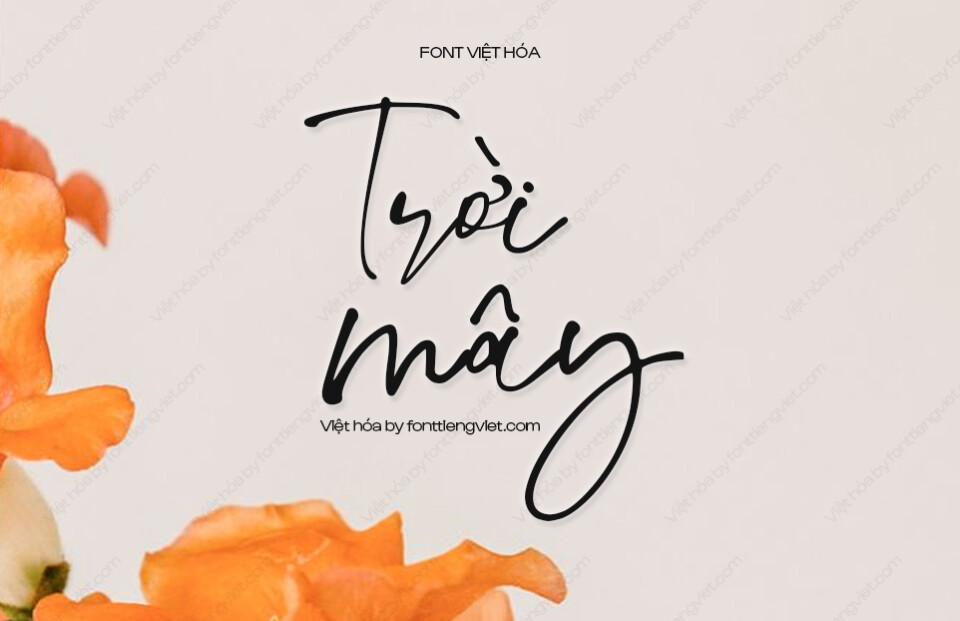
Giới thiệu về bộ Font Việt hóa 1FTV Sidneyland
Trong thế giới đồ họa hiện đại, việc tìm kiếm một bộ Font Chữ vừa mang nét tinh nghịch vừa giữ được sự chuyên nghiệp là điều không dễ dàng. Font Việt hóa 1FTV Sidneyland chính là giải pháp hoàn hảo cho các bạn học sinh và giáo viên khi muốn tạo ra những ấn phẩm học đường sinh động. Với đường nét thanh mảnh nhưng vẫn chắc chắn, bộ phông này giúp truyền tải thông điệp một cách nhẹ nhàng và gần gũi nhất. 1FTV Sidneyland được đội ngũ thiết kế tối ưu hóa hoàn toàn để hiển thị tốt trên các phần mềm soạn thảo văn bản và đồ họa phổ biến hiện nay.
Ưu điểm nổi bật của Font Việt hóa 1FTV Sidneyland
Thiết kế độc đáo và hiện đại
Điểm mạnh nhất của Font Việt hóa 1FTV Sidneyland chính là sự linh hoạt trong ứng dụng. Các ký tự được chăm chút tỉ mỉ, giúp việc đọc trở nên dễ dàng hơn dù trên màn hình máy tính hay khi in ấn. Bộ font này cực kỳ phù hợp để thiết kế bìa sách, nhãn vở, hoặc các bài thuyết trình PowerPoint trong lớp học, mang lại cảm giác vui tươi và tràn đầy năng lượng sáng tạo cho người xem.
Hỗ trợ tiếng Việt hoàn chỉnh
Khác với các bộ font nước ngoài thường bị lỗi dấu khi gõ tiếng Việt, Font Việt hóa 1FTV Sidneyland đã được xử lý kỹ lưỡng về bảng mã. Bạn có thể tự tin sử dụng mọi dấu thanh mà không lo bị nhảy lỗi ký tự, giúp tiết kiệm thời gian chỉnh sửa và đảm bảo tính thẩm mỹ cao nhất cho tác phẩm của mình.
Kết luận và hướng dẫn sử dụng